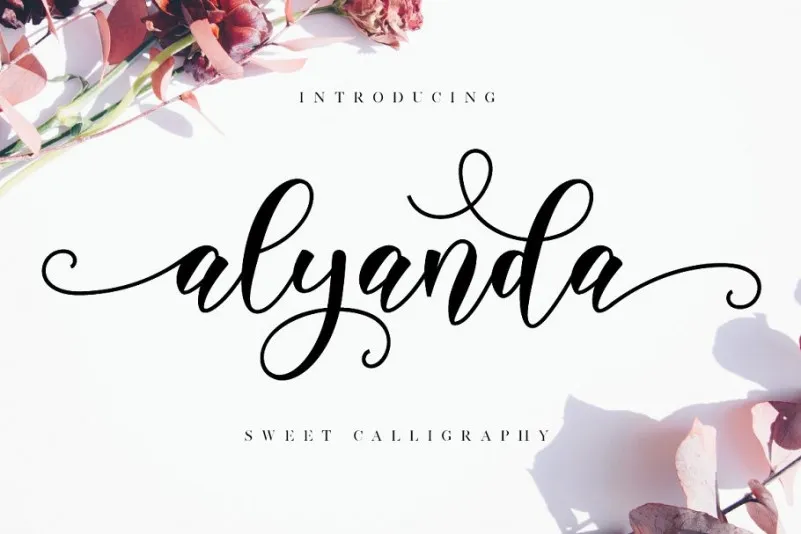
Alyanda Script é uma elegante fonte script que adiciona uma pitada de sofisticação a qualquer projeto visual. Criada pela Nissa Studio, ela traz beleza e modernidade ao seu design, tornando-a perfeitamente adaptável para uma variedade de aplicativos, desde logotipos e convites até capas de livros e cartões de visitas. Seu estilo elegante e sofisticado lhe dá a liberdade de criar designs únicos que se destacam no seu setor. Uma fonte como essa é definitivamente um complemento ideal para seu portfólio, permitindo-lhe expressar sua personalidade única ao adicionar uma dose de originalidade aos projetos em que estiver trabalhando. Não importa o meio ou a aplicação, Alyanda Script tem o potencial de transformar qualquer projeto em algo realmente especial.